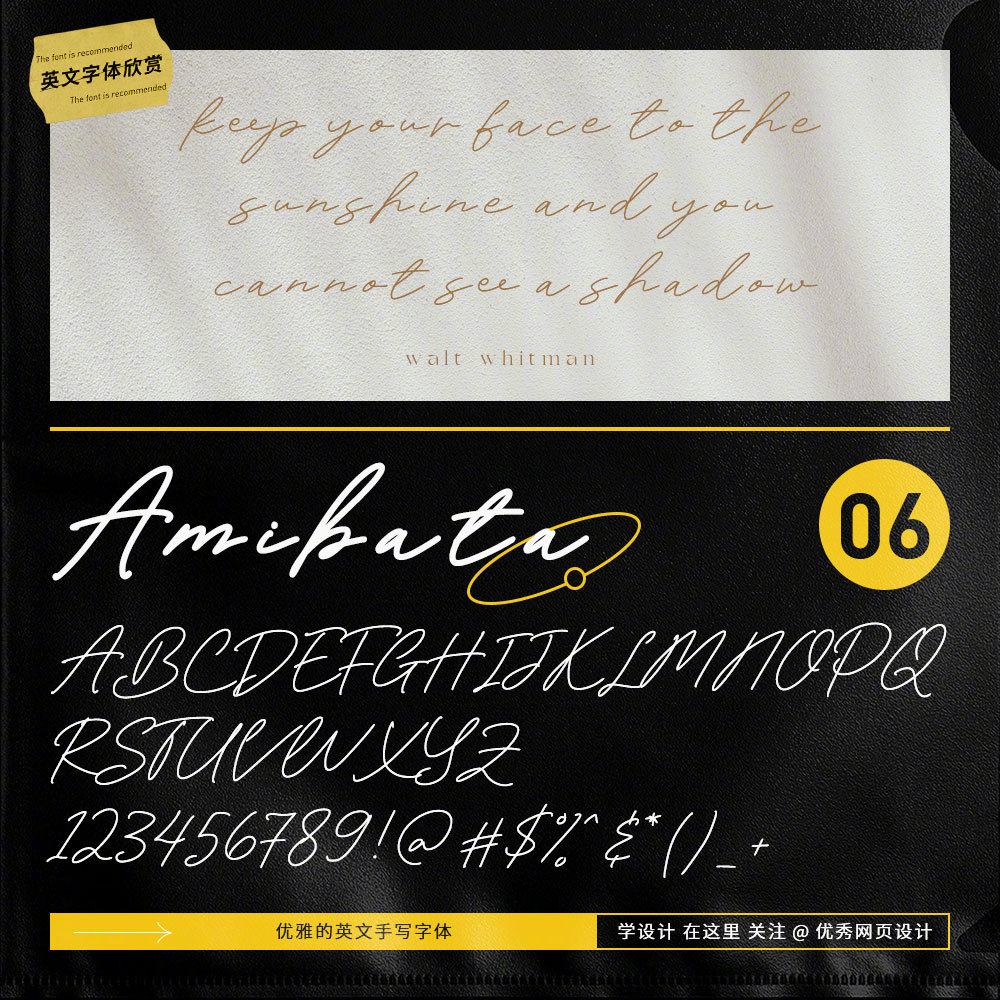
9 phông chữ được gợi ý để sử dụng trong các ấn phẩm như: thích hợp cho thời trang, làm đẹp, tạp chí , máy móc, phông chữ hiện đại, retro và thanh lịch retro phông chữ serif, chữ viết tay tiếng Anh tao nhã để đáp ứng khác nhau với nhu cầu thiết kế của các designer. Mời bạn tham khảo nhé !